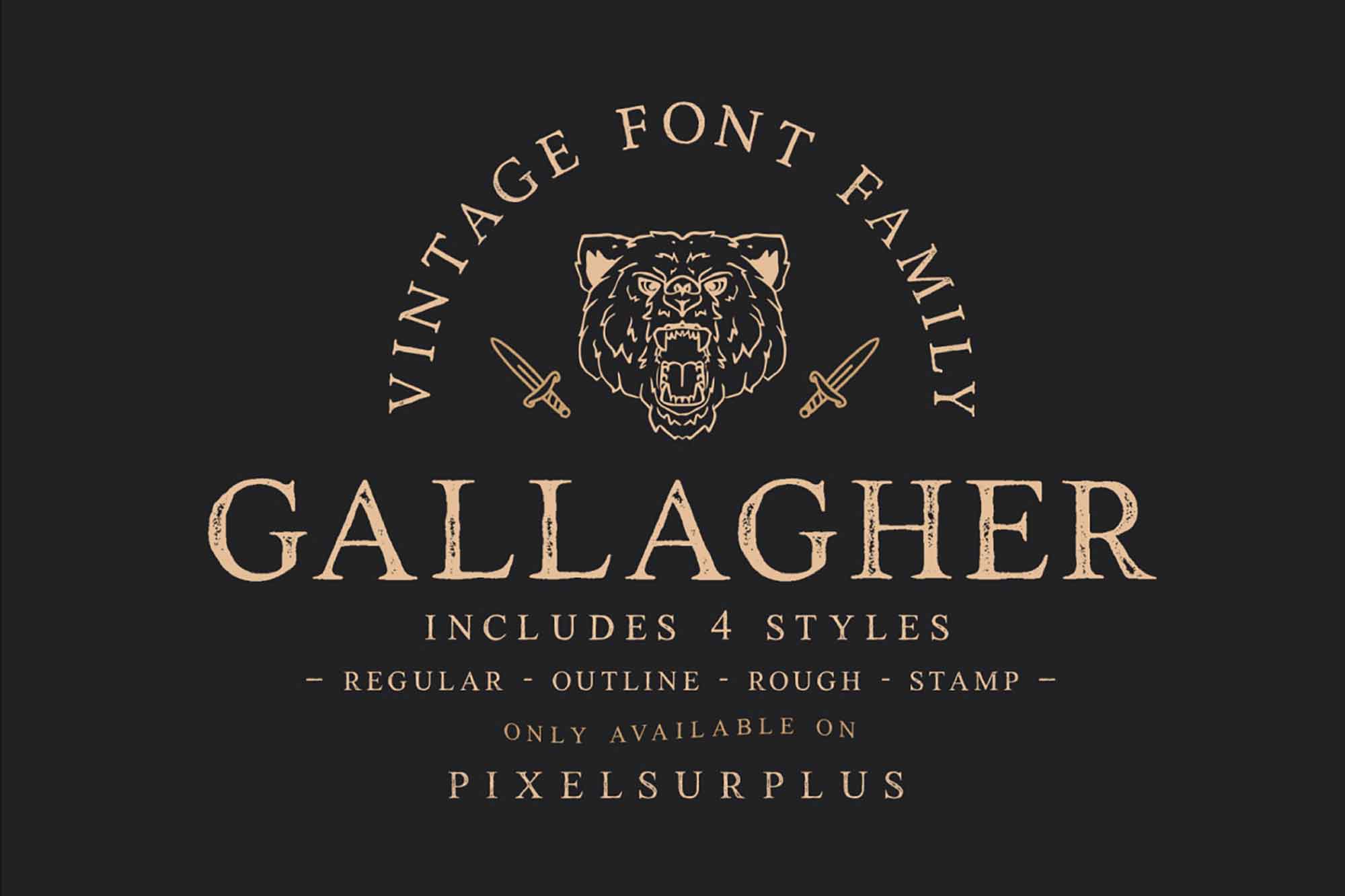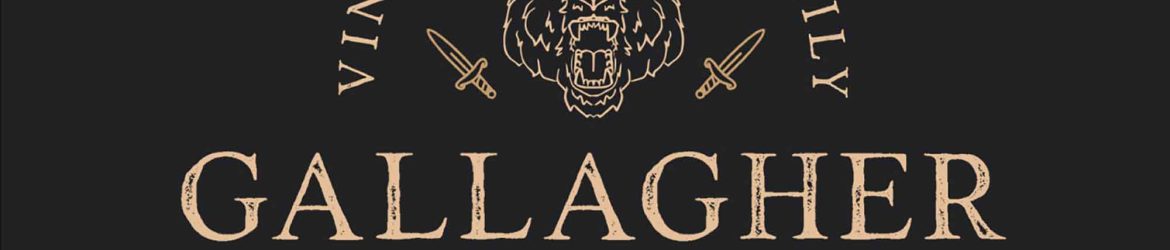
Gallagher Serif Font é uma tipografia elegante e sofisticada, lançada recentemente pela Pixel Surplus, ideal para aqueles que buscam uma mistura de modernidade e vintage em seus projetos de design. A fonte Gallagher possui uma graça única, capaz de trazer uma dose de sofisticação a qualquer tipo de logomarca ou texto. Ela apresenta caracteres vintage em um formato moderno, o que a torna uma opção perfeita para designers que buscam criar um visual atraente e único, que ao mesmo tempo se destaca. Em um mundo cada vez mais digital, ela oferece uma maneira de dar um toque nostálgico e elegante a qualquer projeto gráfico. Seja para uso em logotipos, textos de marca, banners ou sites, a Gallagher Serif Font é uma escolha sólida para quem busca um equilíbrio entre o moderno e o vintage em suas criações.